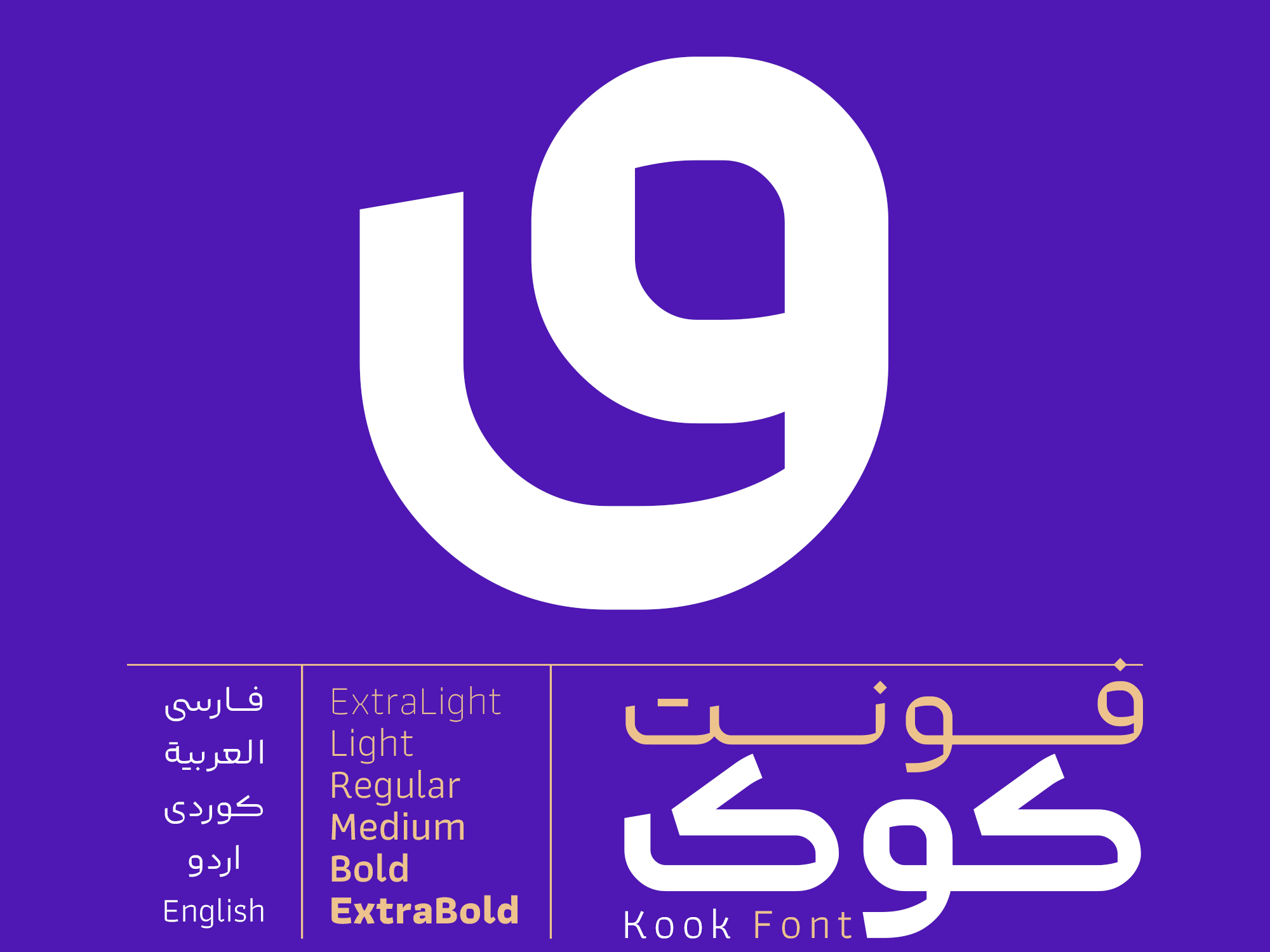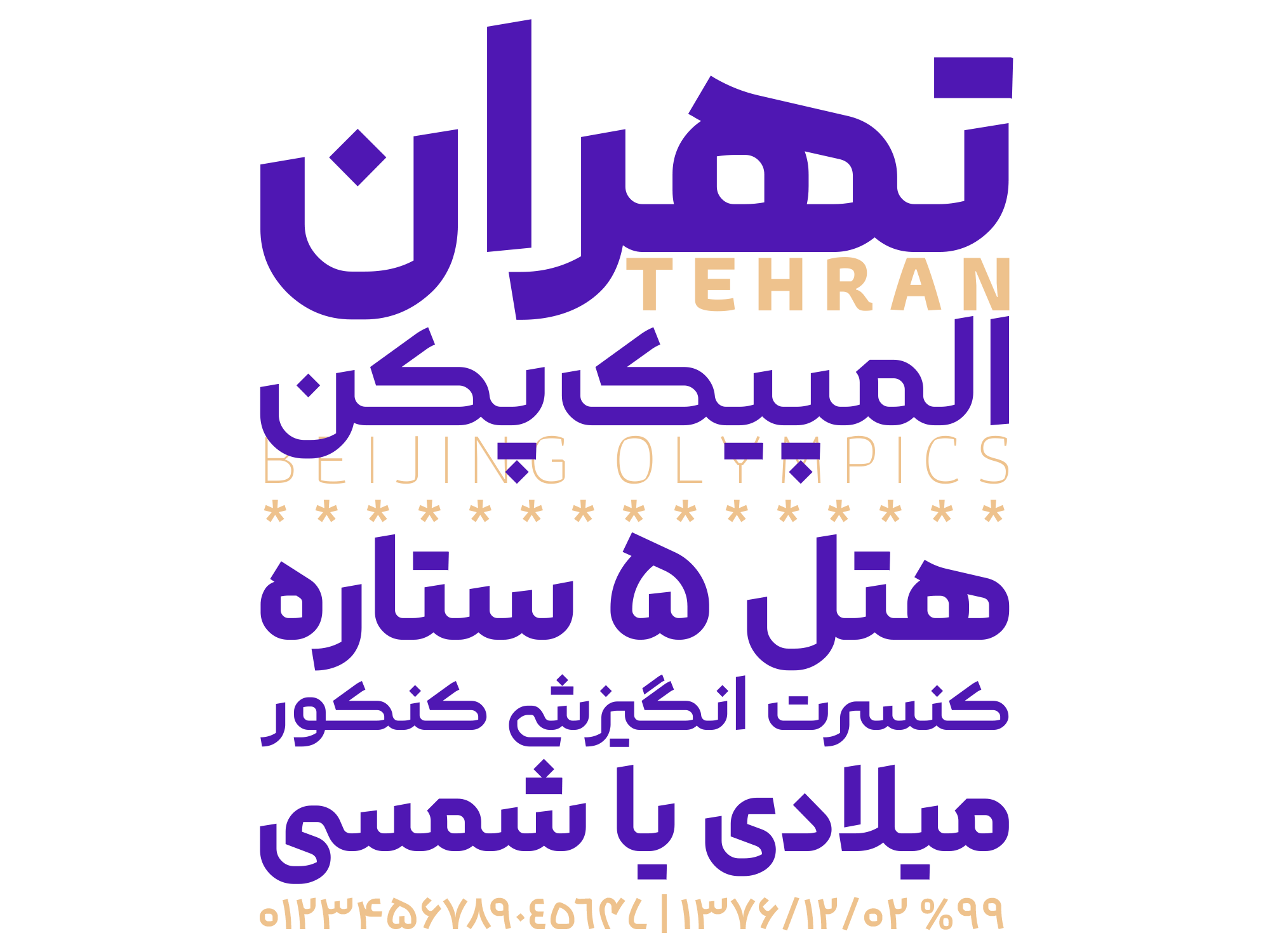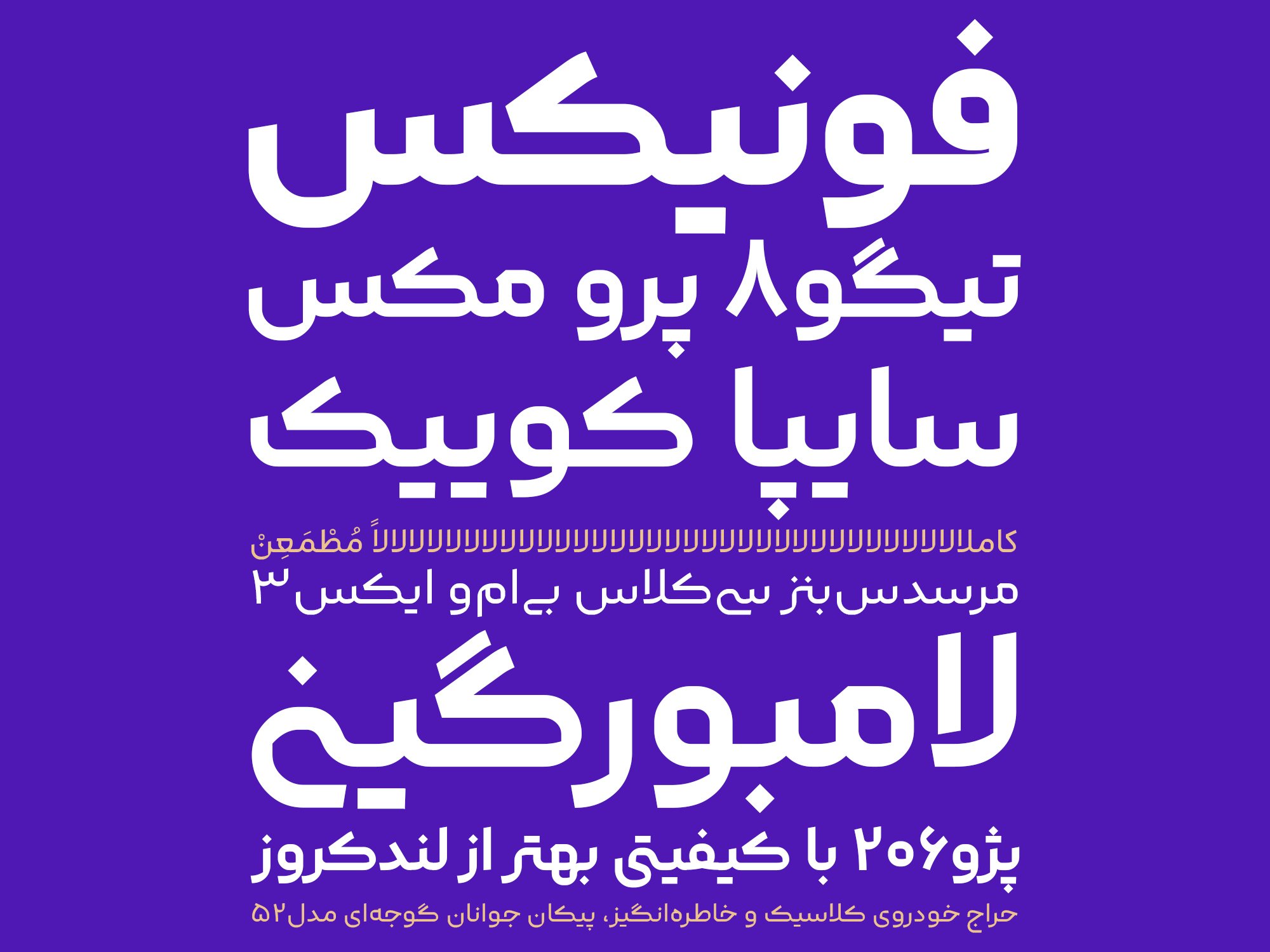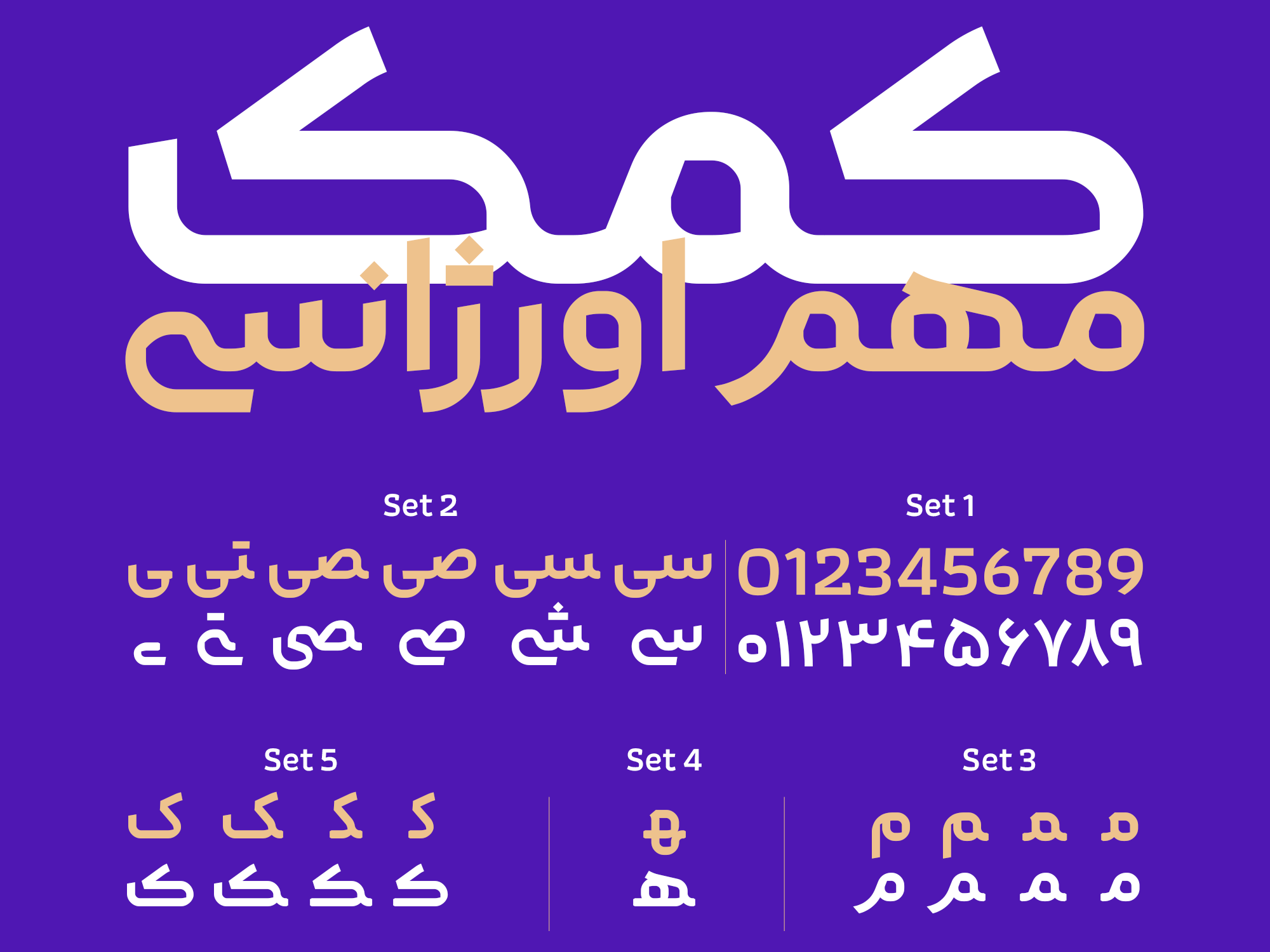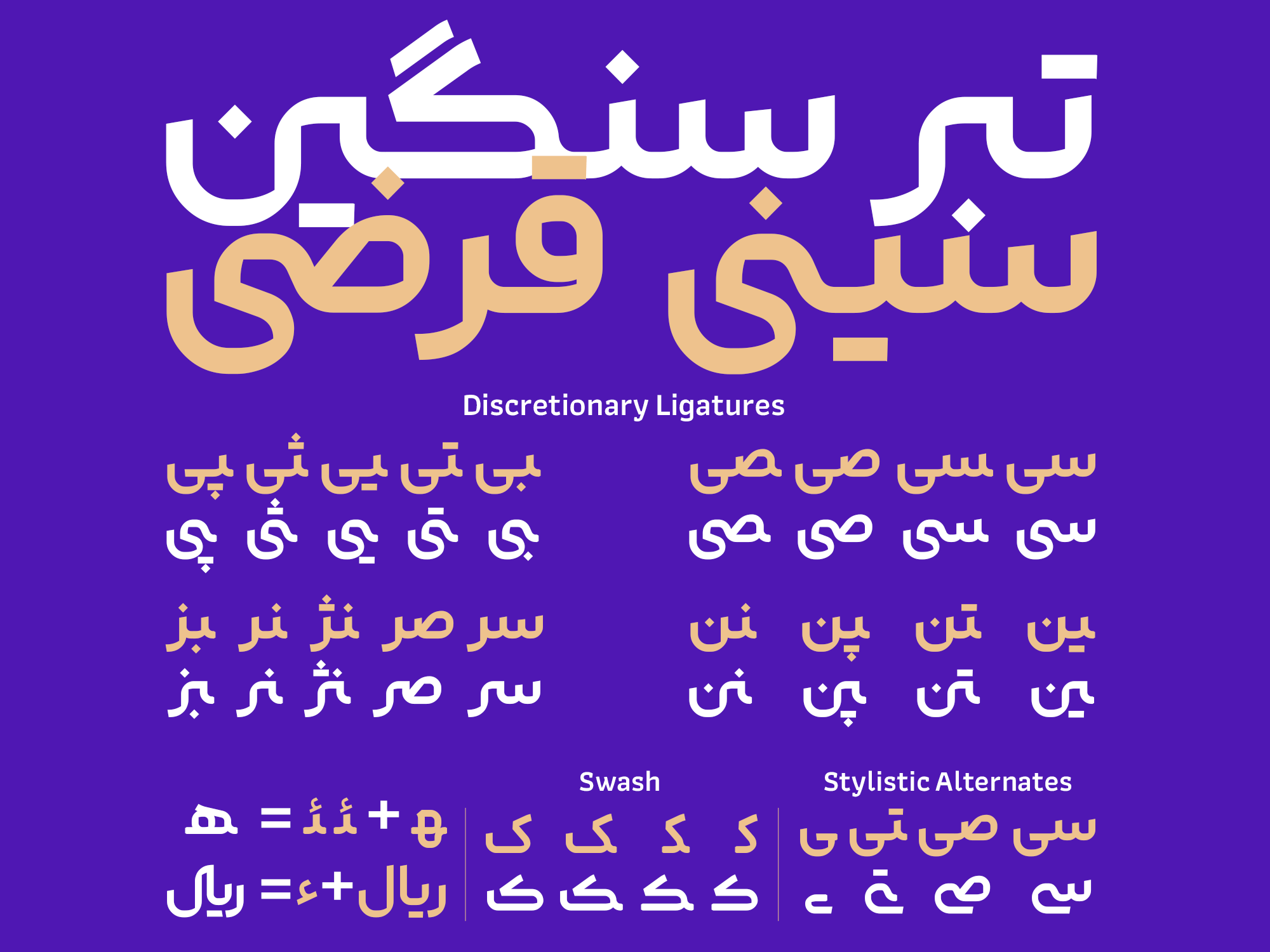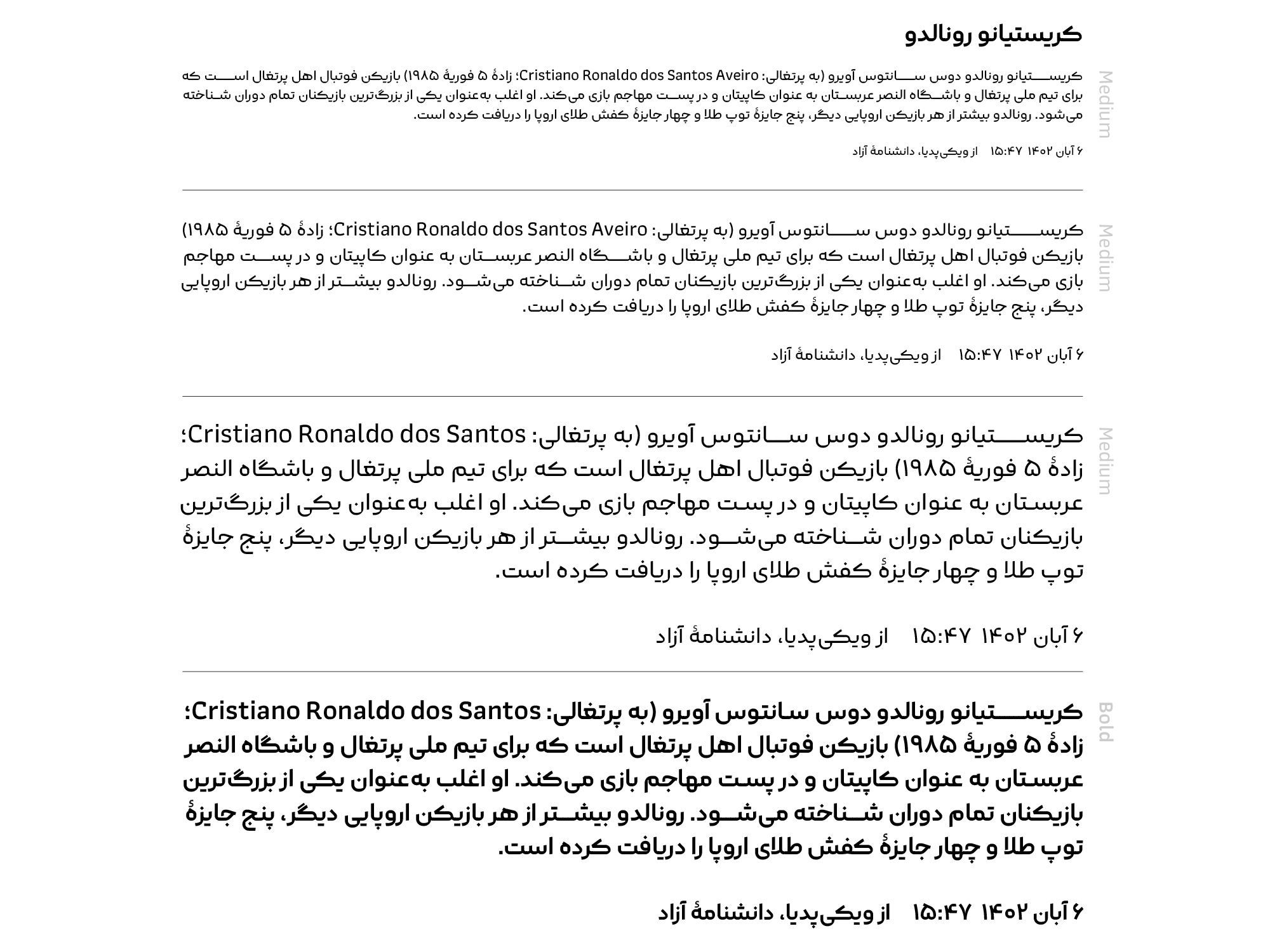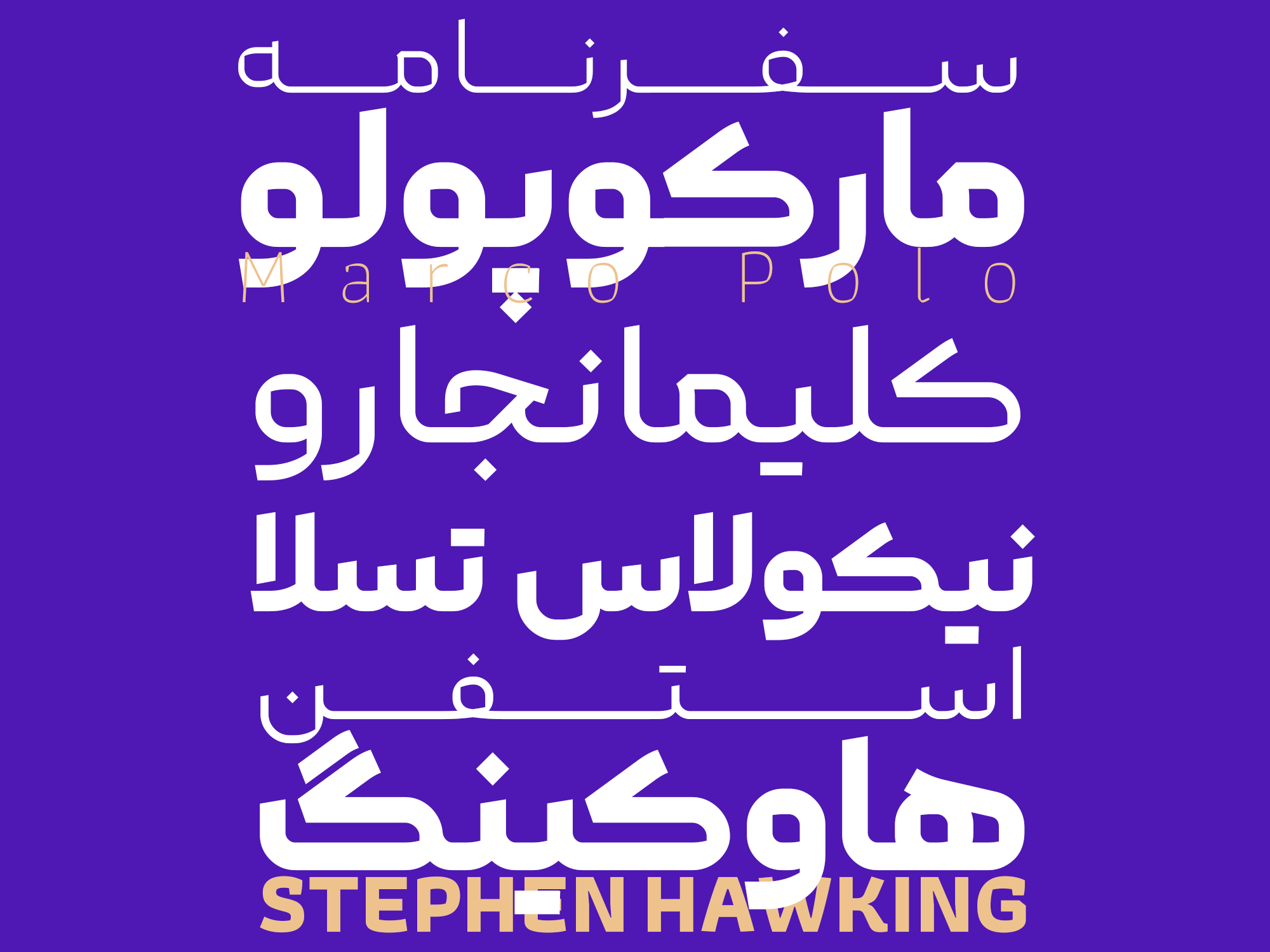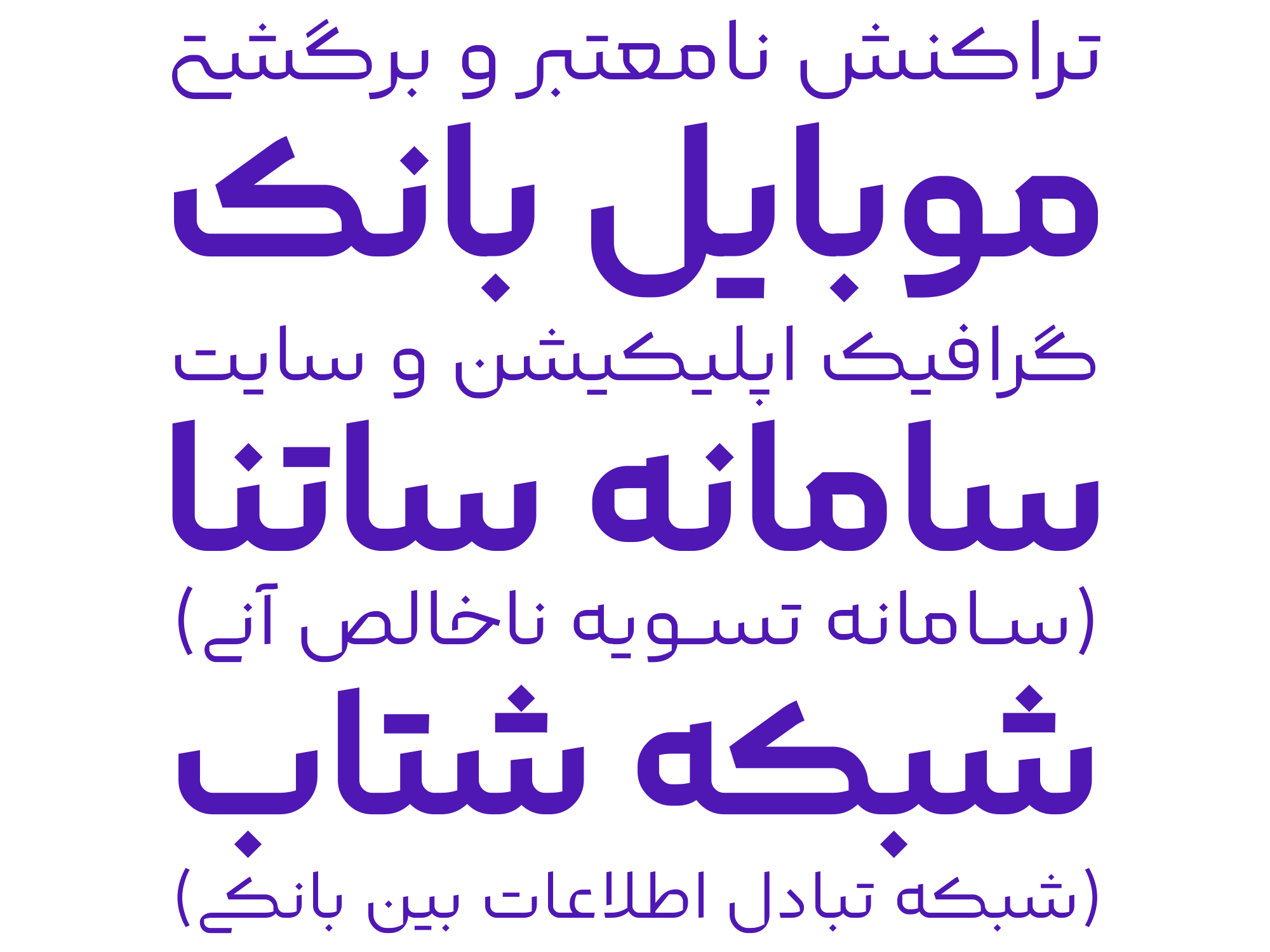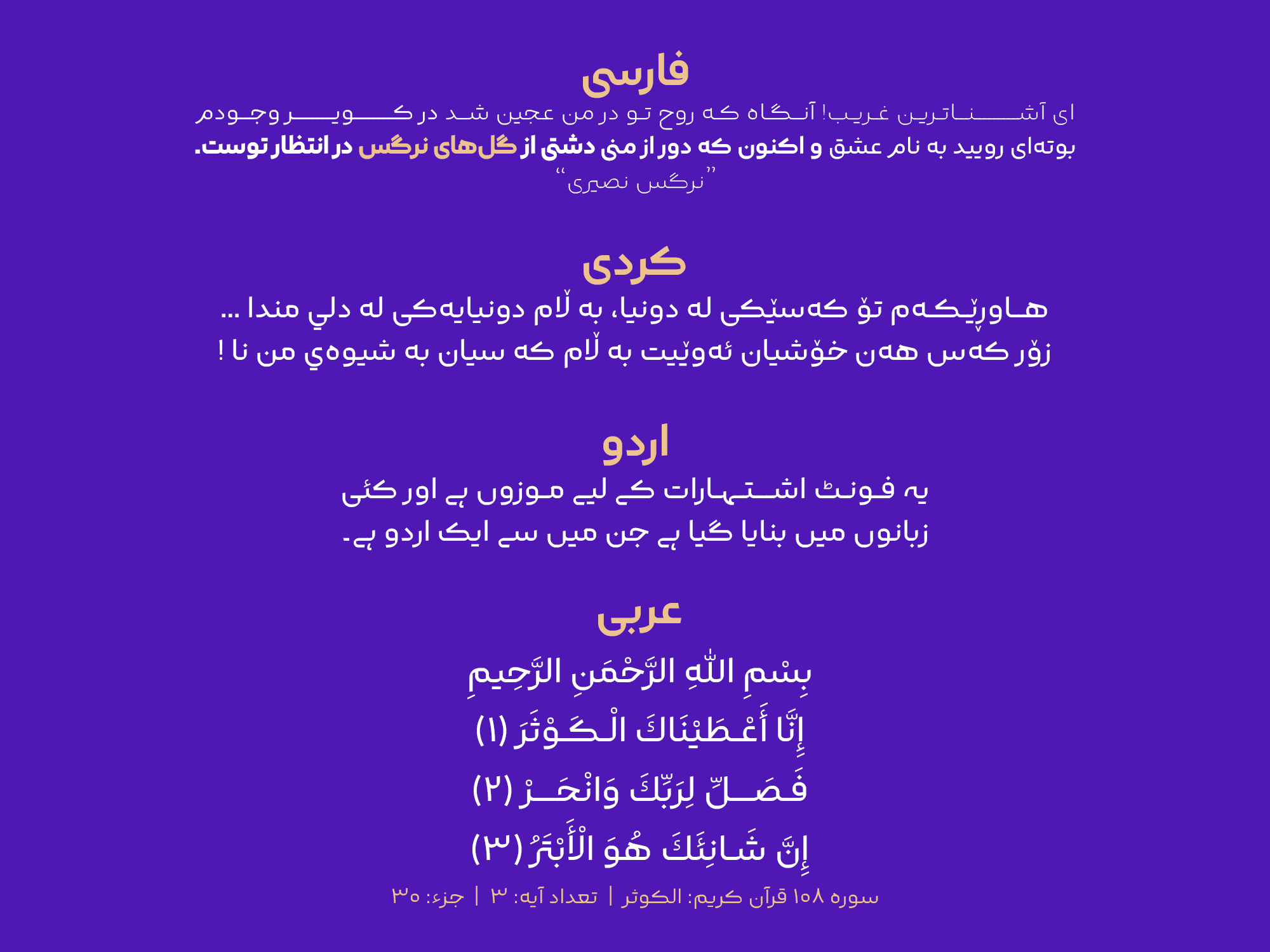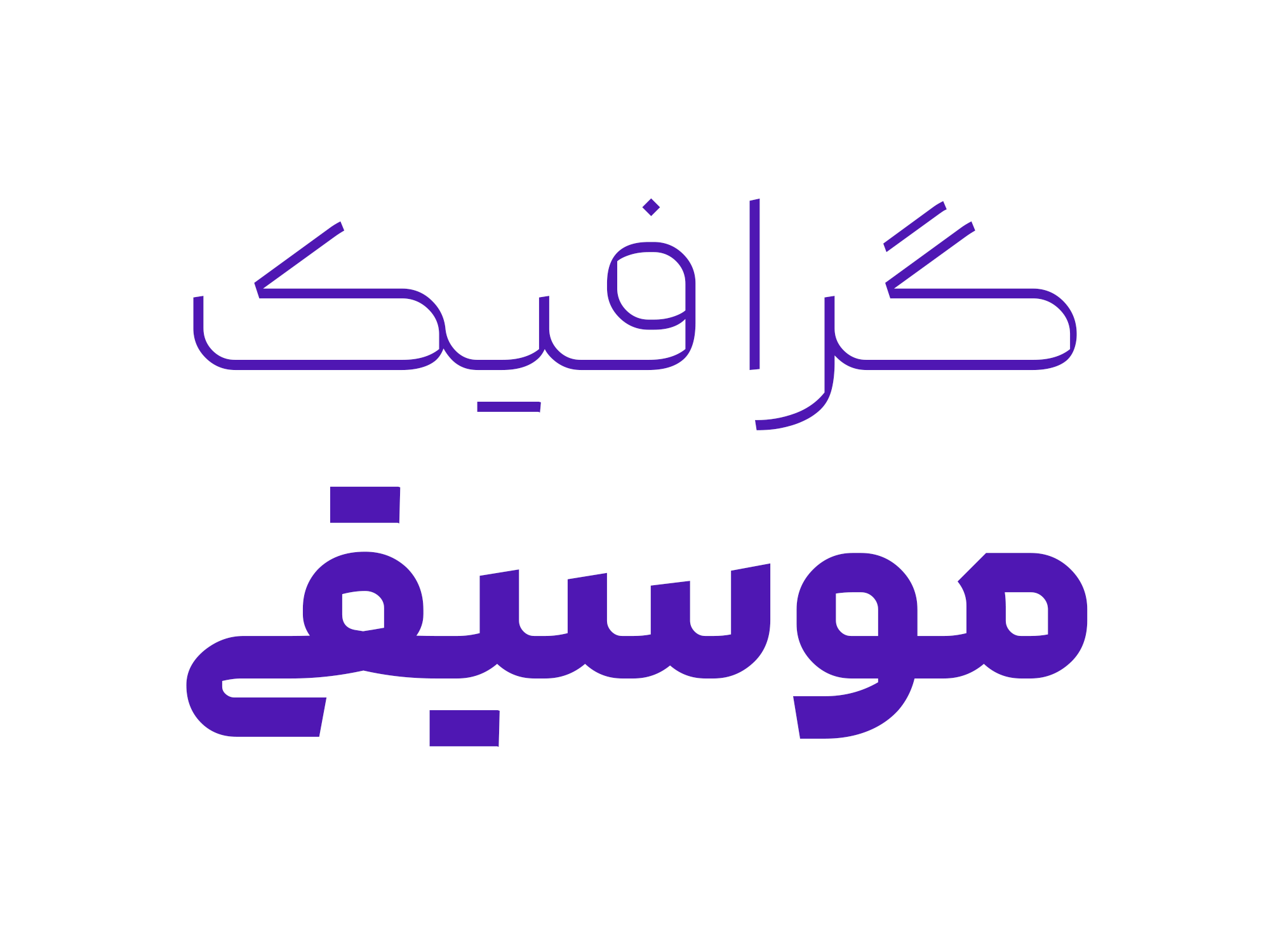
فونت کوک از زبانهای فارسی، عربی، کردی، اردو و انگلیسی پشتیبانی میکند.
شکل گیری فونت کوک:
طراح فونت کوک میگوید: ایده طراحی فونت زمانی به ذهنم رسید که در حال طراحی یک پوستر تبلیغاتی بودم. خواستار فونتی بودم که تلفیقی از خطوط هندسی و خوشنویسی باشد و همچنین همنشینی خوبی با فونتهای لاتین داشته باشد.
طراحی و ساخت نرمافزاری فونت کوک از بهمن 1400 شروع و شهریور 1402 تمام شد.
روند طراحی و کوک کردن حروف:
در آغاز فونت کوک هندسی و ساده بوده، اما در مراحل بعد با اعمال استایل پیچش قلم و چندبار اصلاح و بازبینی به فرم کنونی رسید. تلاش شده است اجزای این فونت با یکدیگر کوک باشد و ظاهر مقبول داشته باشه.
تنوع وزن و زبان در فونت کوک:
فونت کوک دارای 6 وزن (ExtraLight, Light, Regular, Medium, Bold, ExtraBold) است و از زبان فارسی، عربی، کردی، اردو و انگلیسی پشتیبانی میکند.
برای فونت انگلیسی آن از فونت اوپنسورس Athiti استفاده شده است.
سعید حقیقت، از سال ۱۳۹۴ به عنوان تایپوگرافر و طراح کاور موسیقی فعالیت میکند. مهارت او در انجام پروژههای طراحی تایپ، تایپوگرافی و طراحی کاور است.